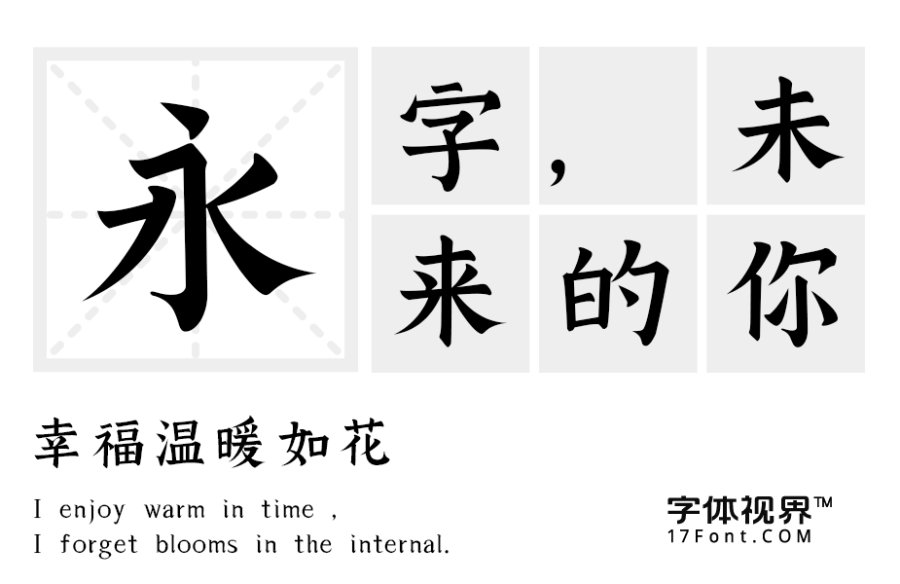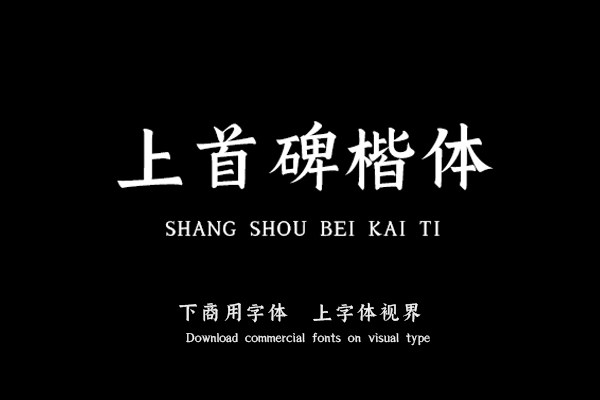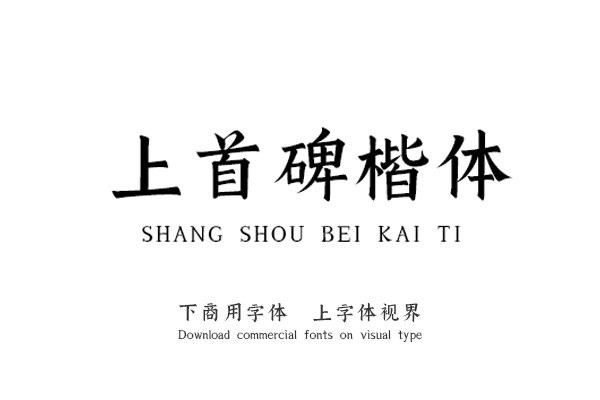
上首碑楷体,简体中文约6763字,字体笔画流畅,横竖笔进行了改良,整体直线处理,字体笔画简洁,形态苍劲有力特点。 适用于搭配标志、广告标语、商业广告等高端属性。购买须知:“下载服务费”与“字体VIP”所获得字体 仅用于个人非商用, 商用请联系付费授权。本字体为电脑用字,手机没有root权限不支持直接手机换字(手机如何root,请自行百度搜索教程)。购买前请先 了解清楚后再付款 ,字体为虚拟产品无法回收 一旦购买不支持退款。